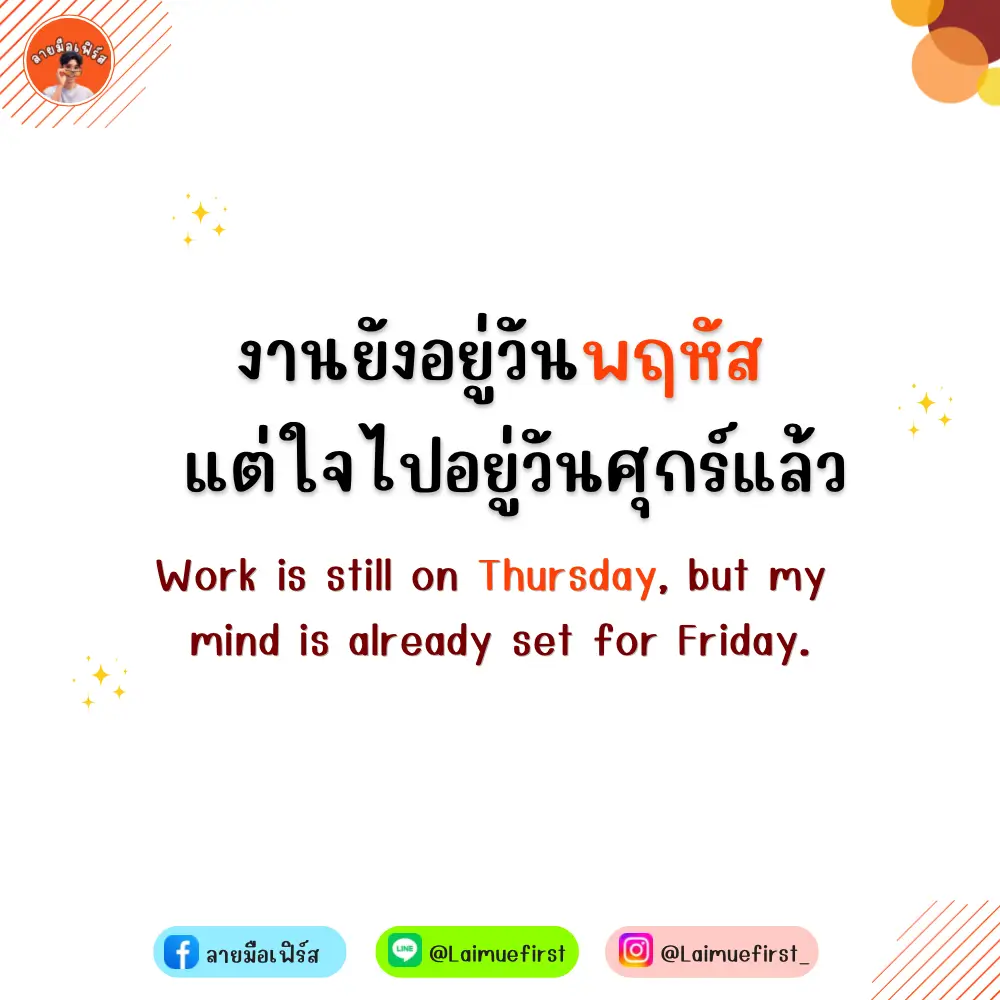
ฟอนต์ลายมือ วันพฤหัส (LMF Wanpharuehat) – แจกฟรีสำหรับทดลองใช้งานแบบส่วนตัว เวอร์ชันทดลอง (Demo)
- ตัวหนังสือปกติ ไม่มีตัวโปร่งปน
วันพฤหัส (LMF Wanpharuehat)